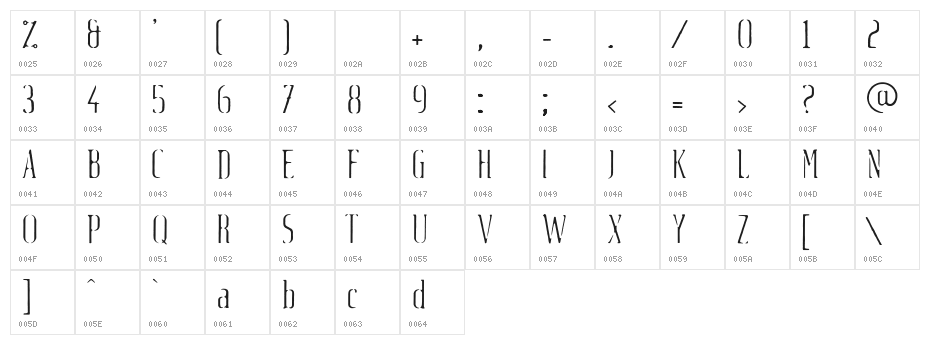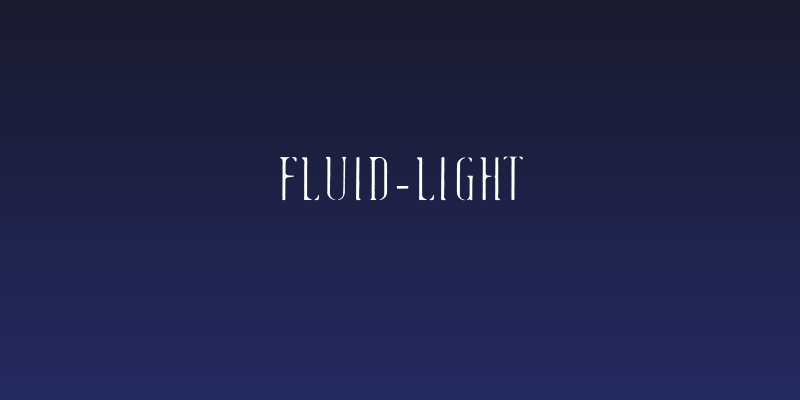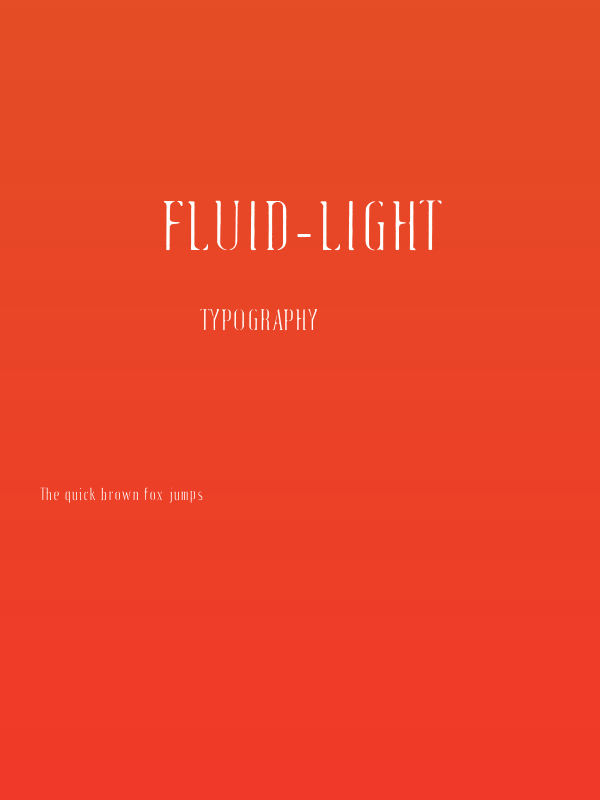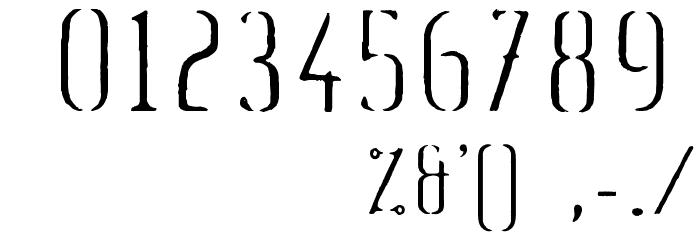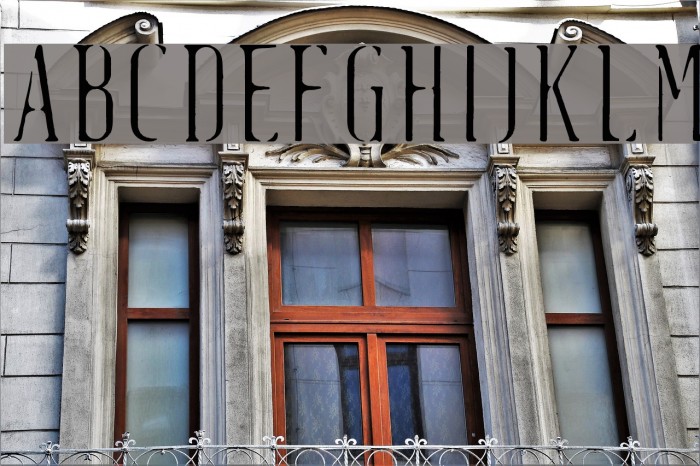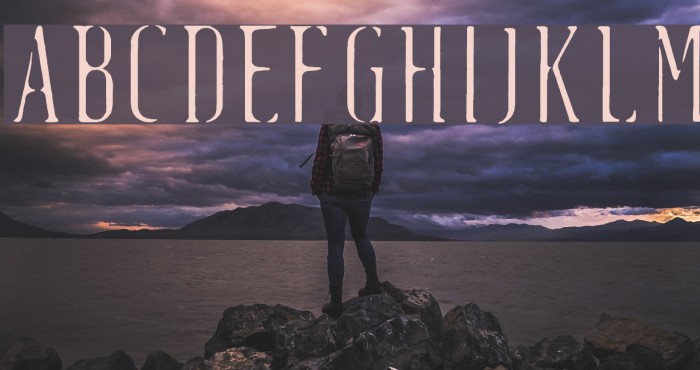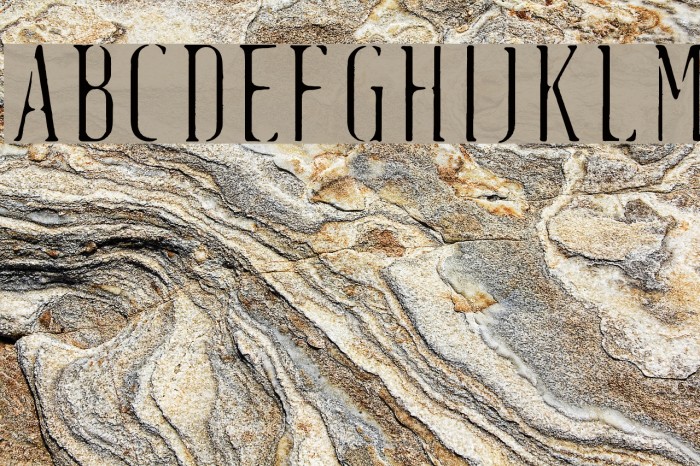
Fluid-light Font
| Kategorien | Distorted Eroded |
| Gesamtstil | Modern, Vintage |
| Vorgeschlagene Projekte | Ideal for branding, editorial design, posters, and packaging where a distinctive and elegant typeface is desired. |